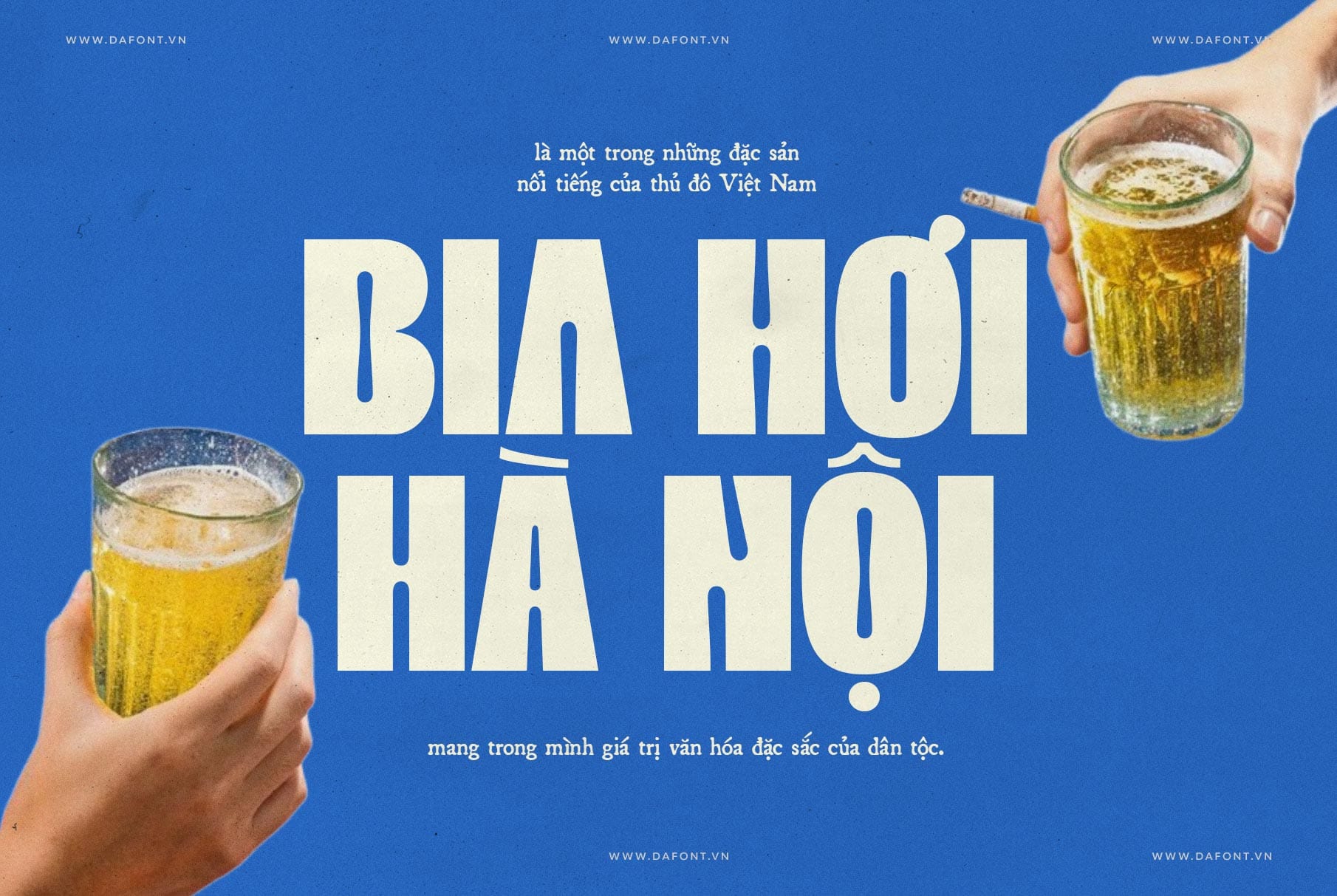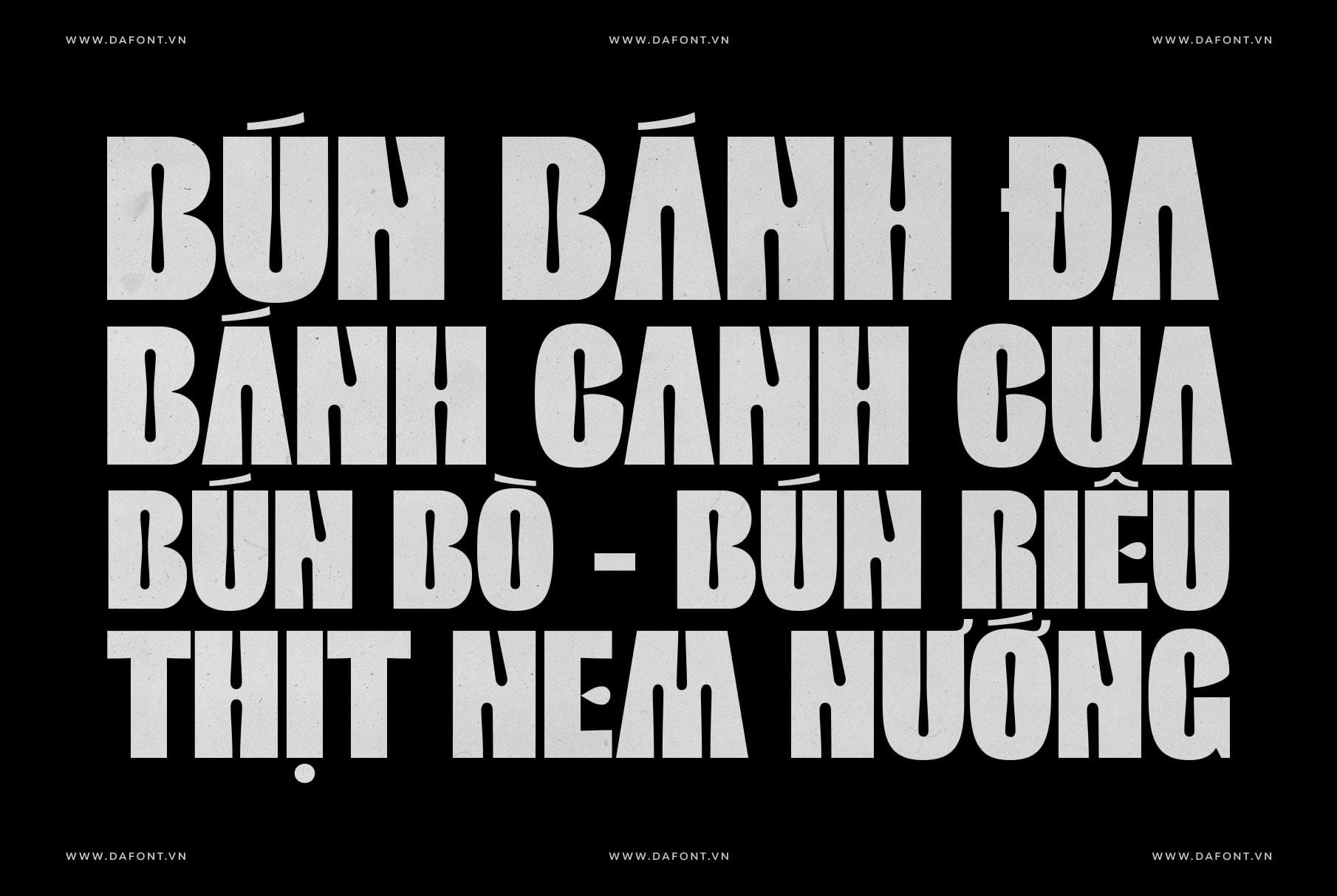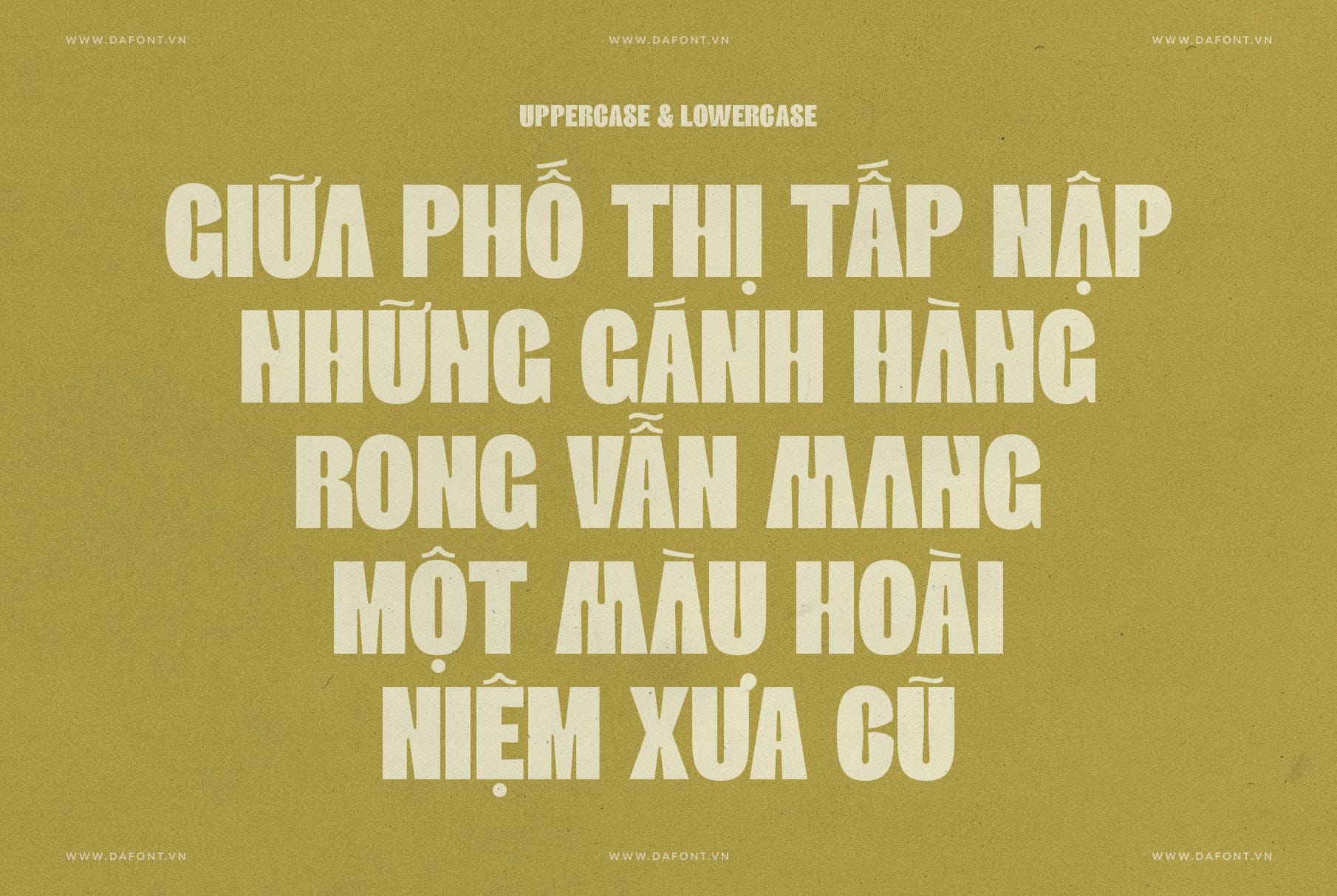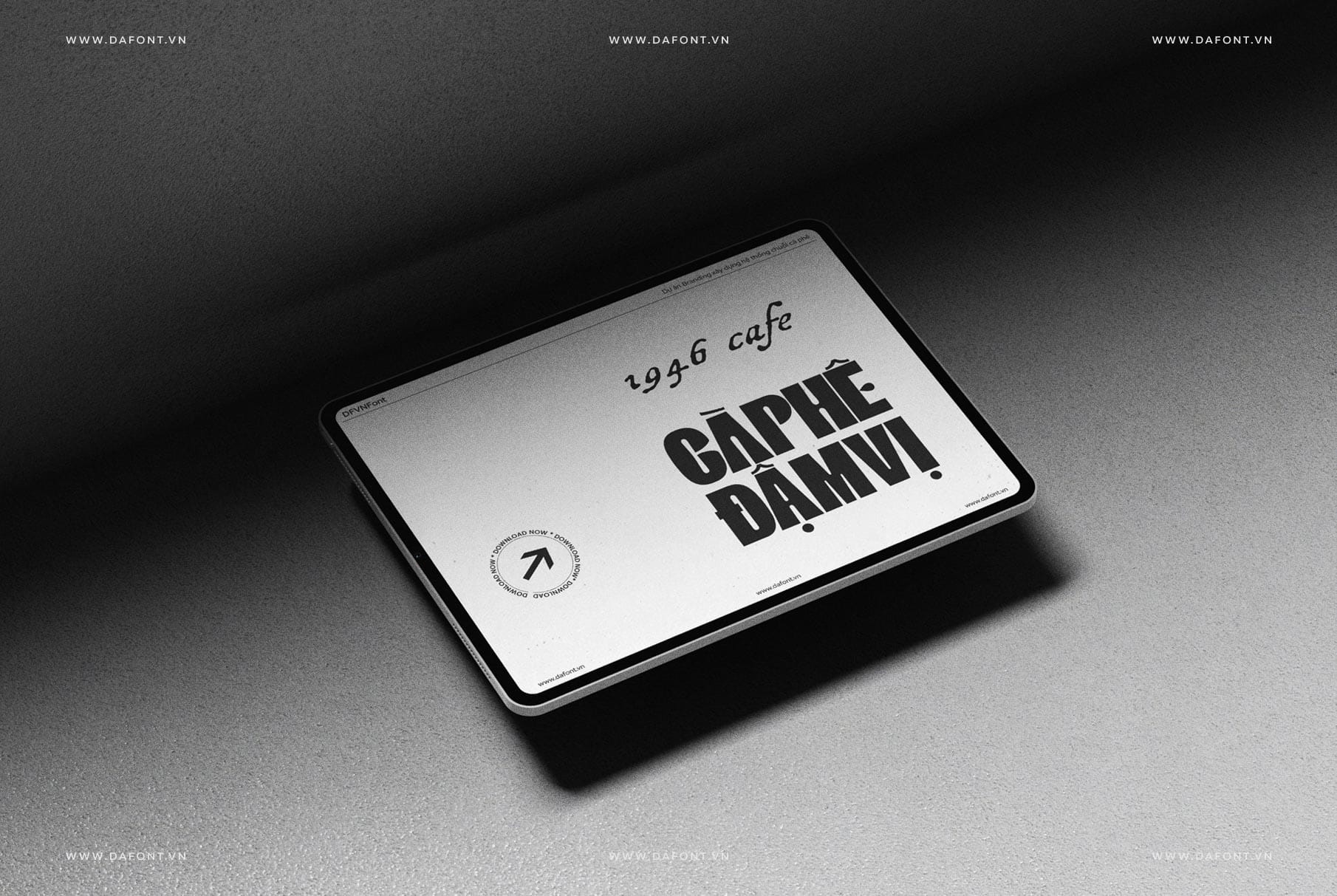
DFVN ED Aughris font – một font chữ hiển thị sans serif hiện đại và đậm chất sáng tạo. Với phong cách tối giản nhưng mạnh mẽ, Aughris không chỉ mang lại sự linh hoạt mà còn giúp các thiết kế trở nên nổi bật và chuyên nghiệp.
ED Aughris là một font chữ sans serif (không chân), được thiết kế với mục tiêu mang đến vẻ đẹp hiện đại và cá tính. Đây là một display font (font hiển thị), lý tưởng cho các yếu tố cần sự chú ý như tiêu đề, poster hay logo. Với đường nét đậm, tối giản nhưng không kém phần tinh tế, Aughris dễ dàng kết hợp với các font khác, tạo nên sự hài hòa và sáng tạo trong mọi bố cục thiết kế.
Đặc điểm nổi bật của DFVN ED Aughris
Aughris không chỉ đẹp mà còn thực dụng, nhờ vào những đặc trưng độc đáo sau:
- Thiết kế đậm và mạnh mẽ: Kiểu chữ đậm của Aughris tạo cảm giác chắc chắn, hiện đại, rất phù hợp cho các tiêu đề lớn hoặc các yếu tố cần gây ấn tượng mạnh.
- Tính linh hoạt cao: Font này dễ dàng phối hợp với các loại font khác như serif, script, mang lại sự đa dạng và sáng tạo cho thiết kế.
- Phong cách tối giản, hiện đại: Aughris phản ánh xu hướng thiết kế đương đại, giúp dự án của bạn luôn tươi mới và hợp thời.
- Ứng dụng đa dạng: Từ logo, poster, thiệp mời, đến thiết kế web hay ấn phẩm in ấn, Aughris đều đáp ứng tốt mọi nhu cầu.
Phù hợp nhiều dự án thiết kế
DFVN ED Aughris không chỉ là một font chữ đẹp mà còn là công cụ mạnh mẽ để nâng cao chất lượng thiết kế. Dưới đây là một số ứng dụng phổ biến:
- Logo và thương hiệu: Với nét chữ đậm và hiện đại, DFVN ED Aughris là lựa chọn hoàn hảo cho các thương hiệu muốn thể hiện sự chuyên nghiệp và cá tính.
- Tiêu đề và poster: Font này rất phù hợp để làm nổi bật tiêu đề trên poster, banner hoặc các ấn phẩm quảng cáo, thu hút ánh nhìn ngay từ cái nhìn đầu tiên.
- Thiết kế web: Sử dụng Aughris cho các tiêu đề hoặc điểm nhấn trên website giúp tăng sự tương phản và làm nổi bật nội dung quan trọng.
- Ấn phẩm sáng tạo: Từ thiệp mời, trích dẫn in ấn đến thiết kế áo thun, Aughris mang lại vẻ ngoài sang trọng và độc đáo.
DFVN ED Aughris – Độc đáo và nổi bật
Aughris là sự kết hợp hoàn hảo giữa phong cách hiện đại, tối giản và linh hoạt, giúp bạn tạo ra các thiết kế ấn tượng và chuyên nghiệp. Dù bạn là nhà thiết kế đồ họa, chủ doanh nghiệp muốn xây dựng thương hiệu, hay chỉ đơn giản là người yêu thích typography, Aughris đều là một lựa chọn không thể bỏ qua.